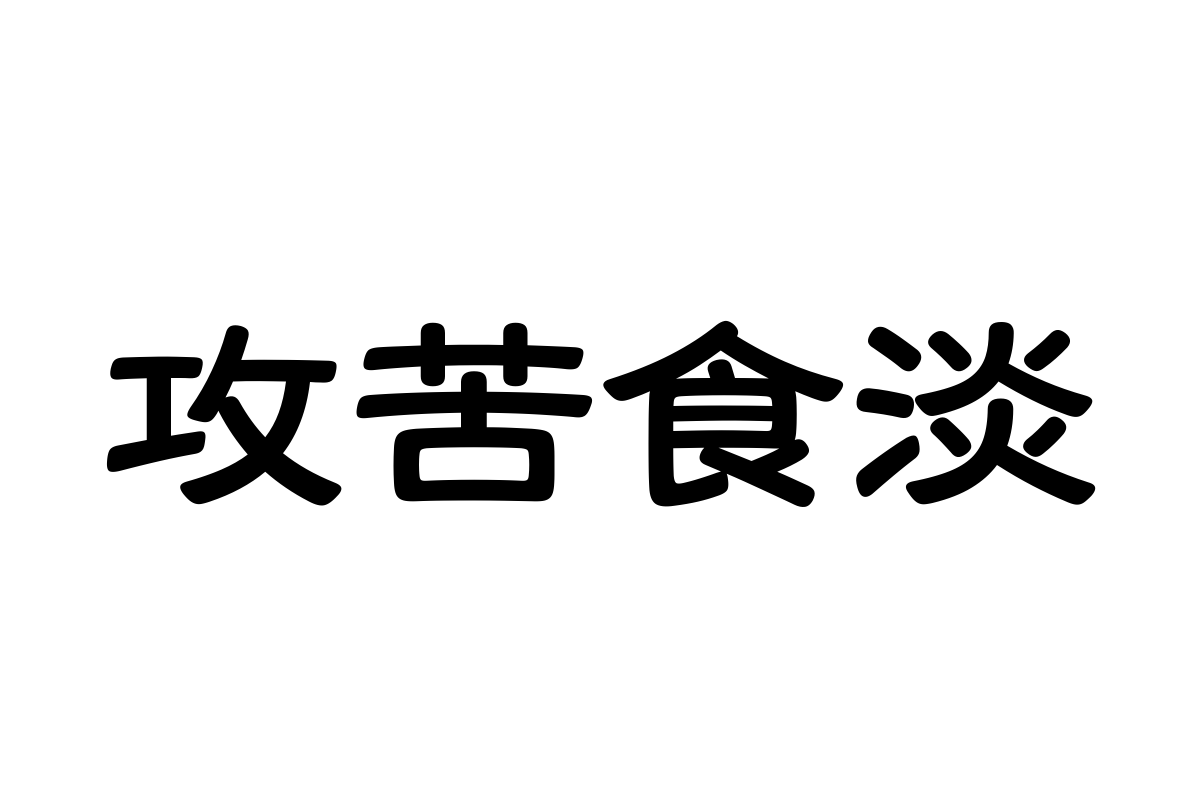
汉仪玉筋隶75繁体字体是一款由汉仪公司设计的一款中文字体,主要用于书法和艺术设计。这款字体的特点是笔画流畅,结构严谨,具有很高的艺术价值。
汉仪玉筋隶75繁体字体的特点如下:
1. 笔画流畅:这款字体的笔画线条流畅自然,给人一种优美的视觉效果。
2. 结构严谨:这款字体的结构严谨,每个笔画都经过精心设计,使得整体效果更加和谐统一。
3. 艺术性强:这款字体具有很强的艺术性,适合用于书法、绘画、广告设计等领域,能够提升作品的整体美感。
4. 可读性好:虽然这款字体的艺术性强,但其可读性也很好,适用于各种场合的文字设计。
总的来说,汉仪玉筋隶75繁体字体是一款非常优秀的中文字体,无论是在书法还是艺术设计领域都能发挥出很好的效果。